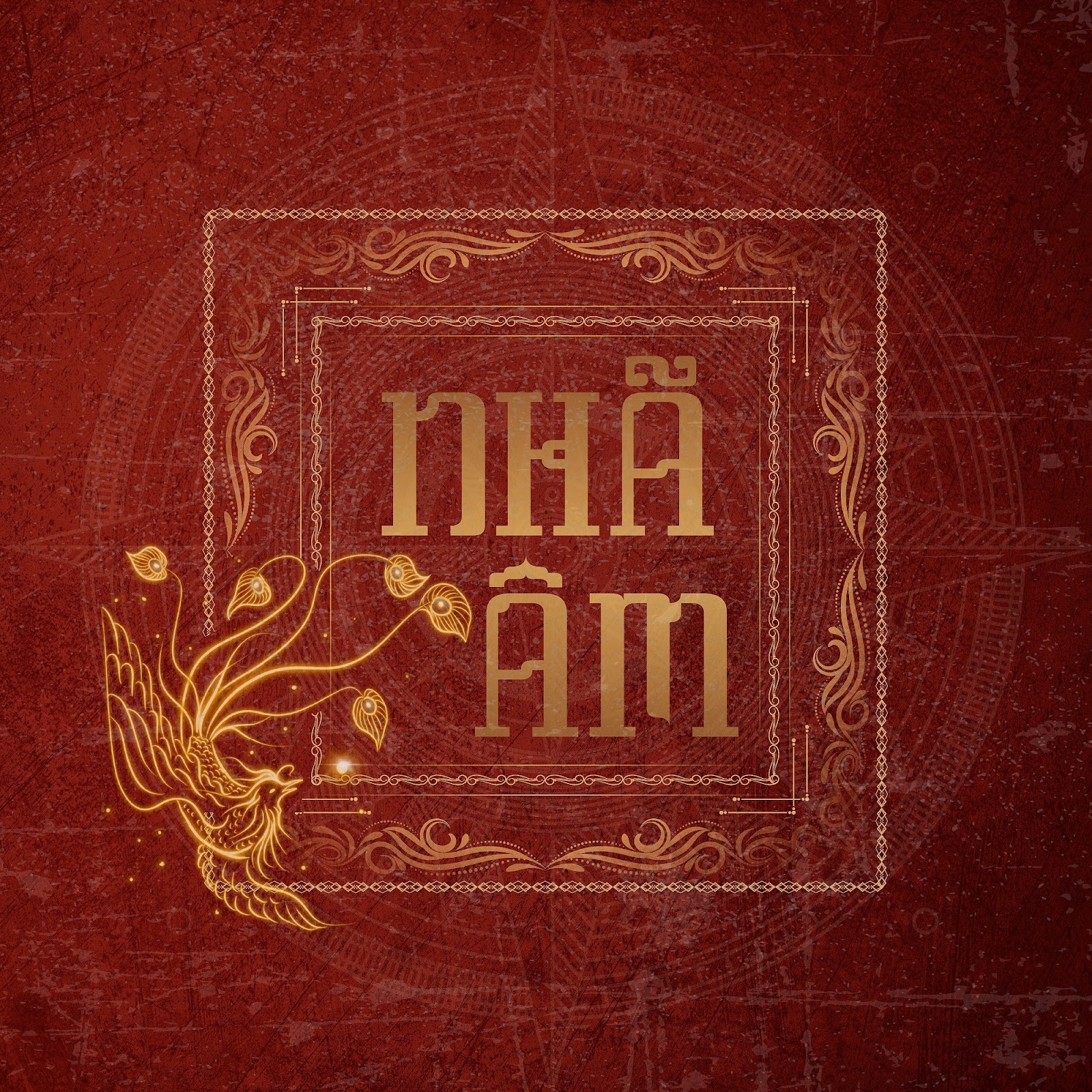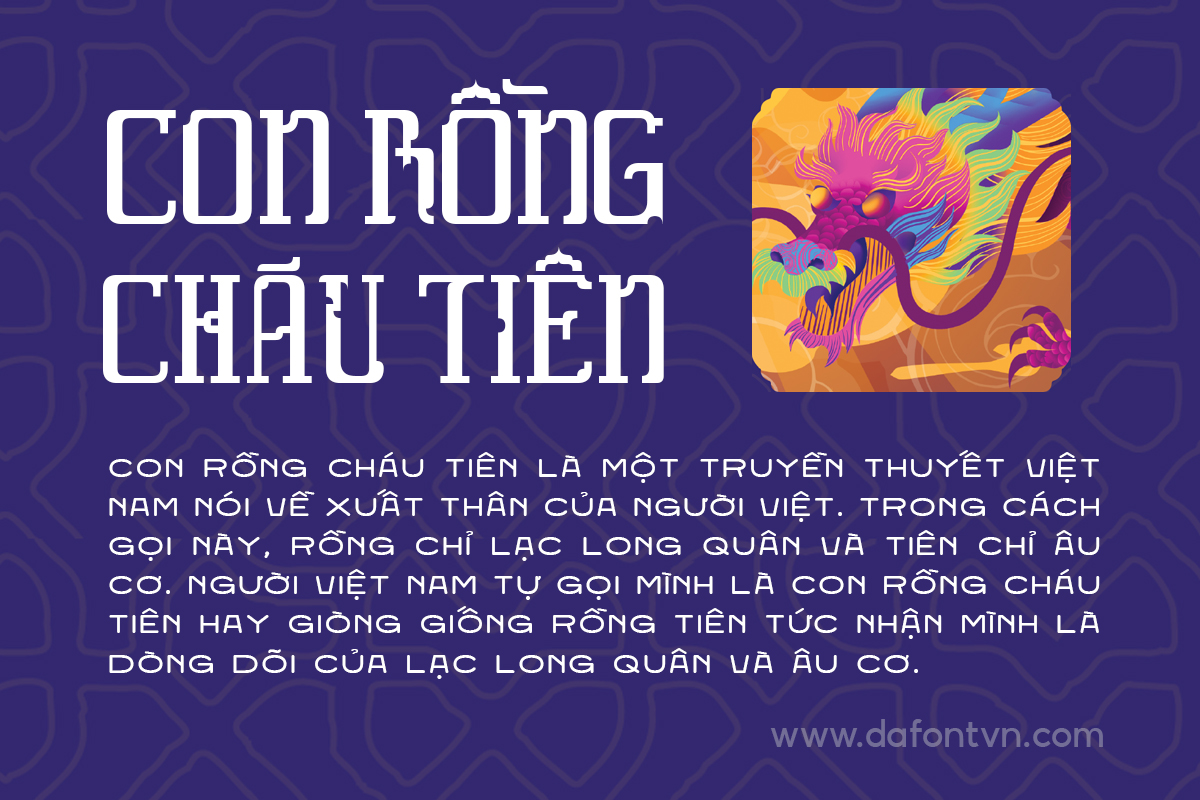
Font Việt Hóa Daybreaker – 1 chiếc font đẹp
Font Việt Hóa Daybreaker – là một font chữ rất đẹp, khá phù hợp cho những thiết kế cổ truyền mang hơi hướng dân tộc và văn hóa truyền thống hoặc bất kỳ thiết kế nào khác. Font được việt hóa đầy đủ bởi LNTH và được tối ưu lại.
Font việt hóa phù hợp làm cổ trang, xưa cũ